Sonar — австралийская студия, которая делает саунд-дизайн и пишет музыку для кино, рекламы, телевидения и новых медиа. Sonar сотрудничали, например, с Nike, Samsung, McDonald’s и продакшн-компаниями Netflix и Disney.
Для заголовков на сайте студии дизайнер Никколо Миранда выбрал Stratos студии Production Type и Ayer студии Commercial Type, а для наборного текста — Messina Sans студии Luzi Type и HK Guise студии Hanken Design Co.
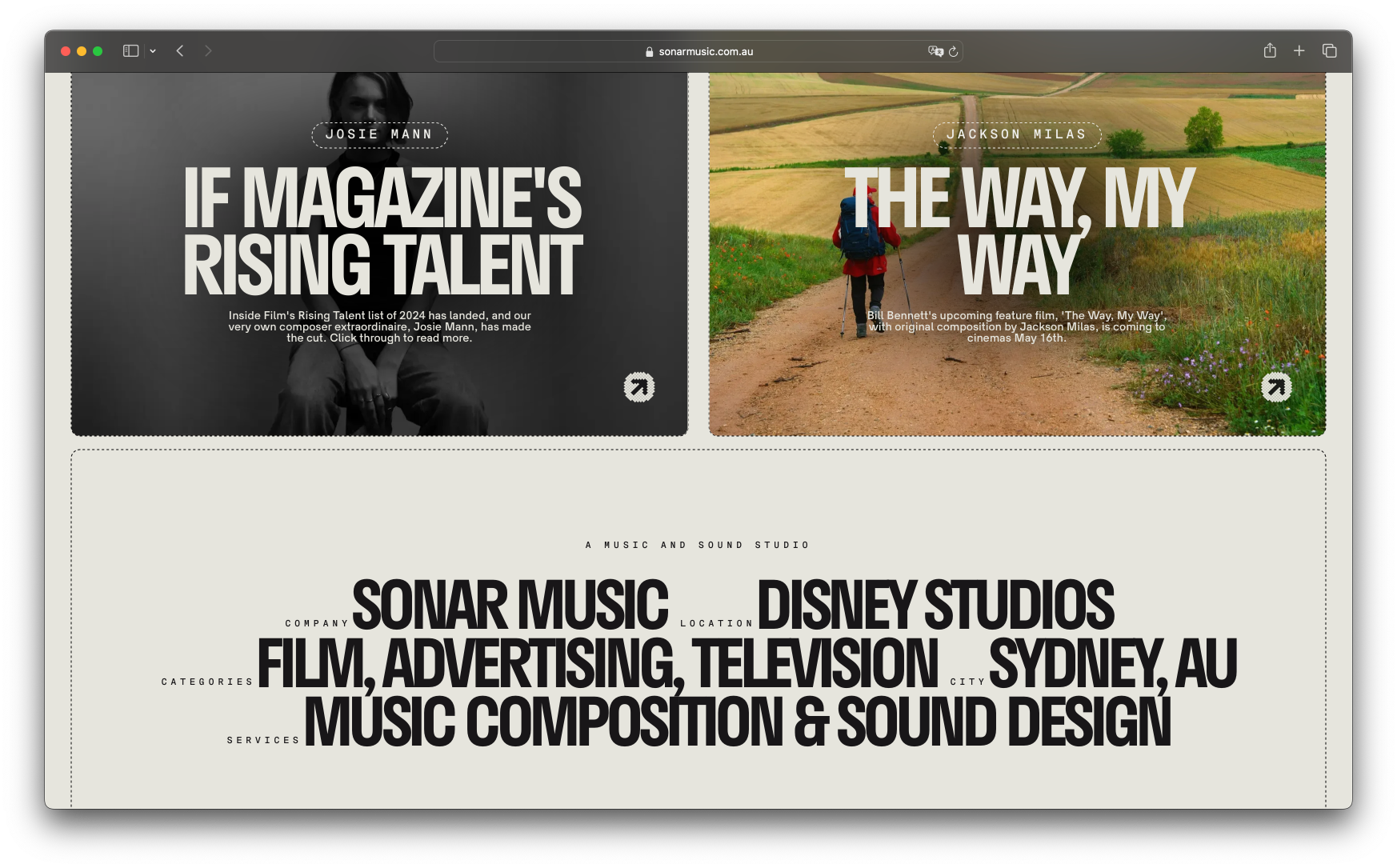
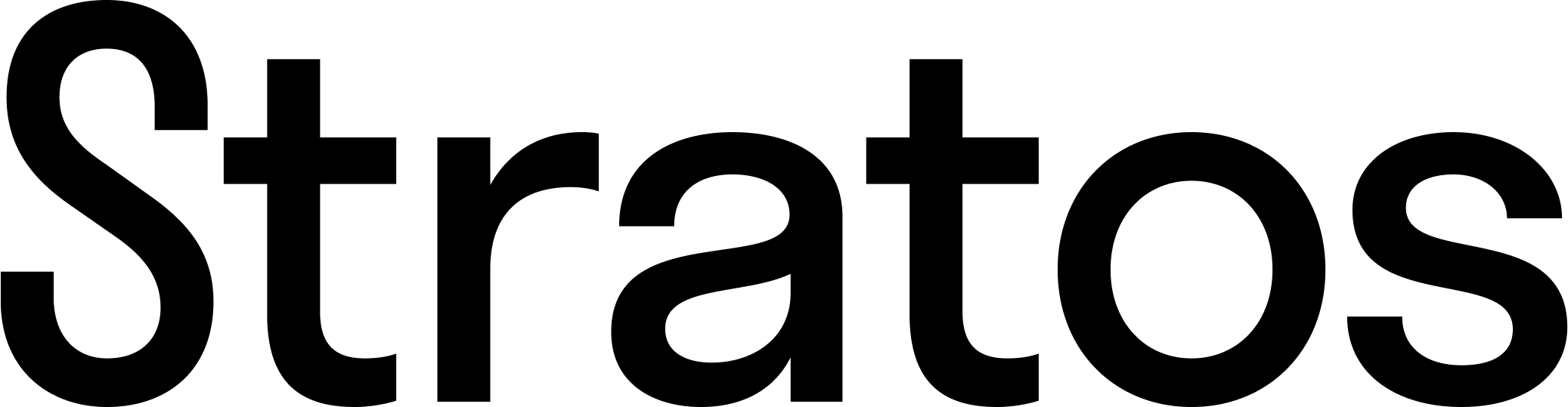
Stratos — геометрический гротеск с палитрой из десяти начертаний от Thin